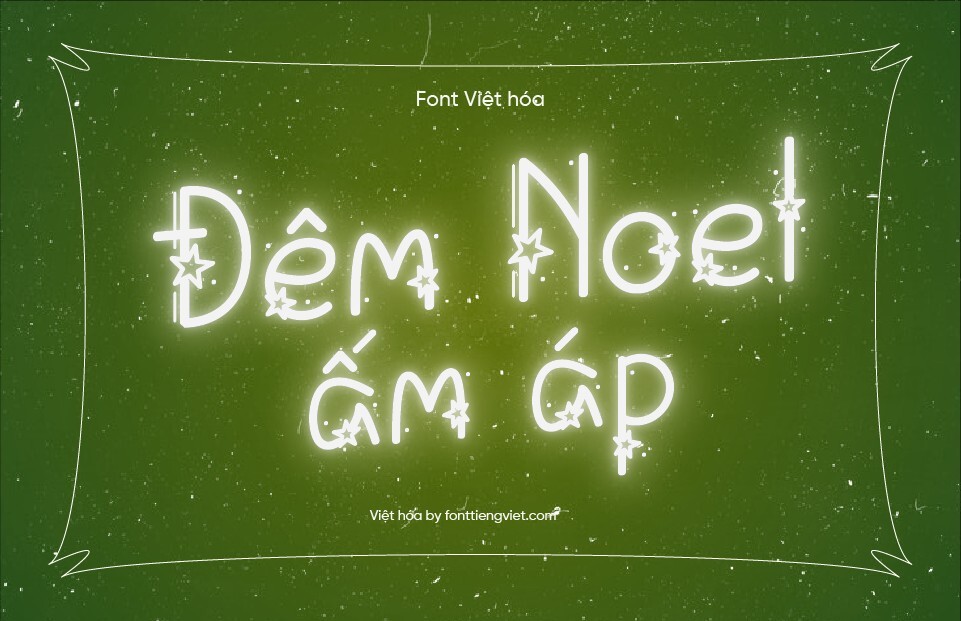
Tải Font Việt hóa 1FTV VIP Starry Fayez – Giáng sinh miễn phí cho thiết kế Noel rực rỡ
Mùa lễ hội cuối năm đang đến gần, nhu cầu tìm kiếm một bộ Font Chữ mang đậm không khí lễ hội ngày càng tăng cao. Trong số đó, Font Việt hóa 1FTV VIP Starry Fayez – Giáng sinh nổi lên như một lựa chọn hoàn hảo nhờ phong cách thiết kế độc đáo và đầy sáng tạo. Đây là bộ phông chữ được tinh chỉnh kỹ lưỡng, giúp các nhà sáng tạo nội dung và học sinh dễ dàng thiết kế những ấn phẩm đẹp mắt phục vụ cho mục đích giáo dục cũng như trang trí sự kiện trường lớp.
Đặc điểm nổi bật của Font Việt hóa 1FTV VIP Starry Fayez – Giáng sinh
Thiết kế đậm chất nghệ thuật và hiện đại
Bộ font này gây ấn tượng mạnh mẽ với các đường nét thanh mảnh nhưng vẫn giữ được sự chắc chắn. Điểm nhấn đặc biệt nằm ở các chi tiết cách điệu mô phỏng ánh sao lấp lánh và bông tuyết, tạo nên cảm giác ấm áp và huyền ảo của đêm Noel. Với tính năng Việt hóa hoàn chỉnh, bạn sẽ không còn lo lắng về lỗi hiển thị dấu tiếng Việt, đảm bảo văn bản luôn giữ được sự đồng nhất và tính thẩm mỹ cao nhất trên mọi thiết bị.
Ứng dụng đa dạng trong học tập và thiết kế
Bên cạnh việc trang trí, bộ chữ này còn rất phù hợp để làm tiêu đề bài giảng, thiết kế thiệp chúc mừng hoặc poster cho các hoạt động ngoại khóa tại trường học. Sự kết hợp giữa nét chữ nghệ thuật và chủ đề Giáng sinh giúp thông điệp truyền tải trở nên sinh động, thu hút sự chú ý của người xem ngay từ cái nhìn đầu tiên.